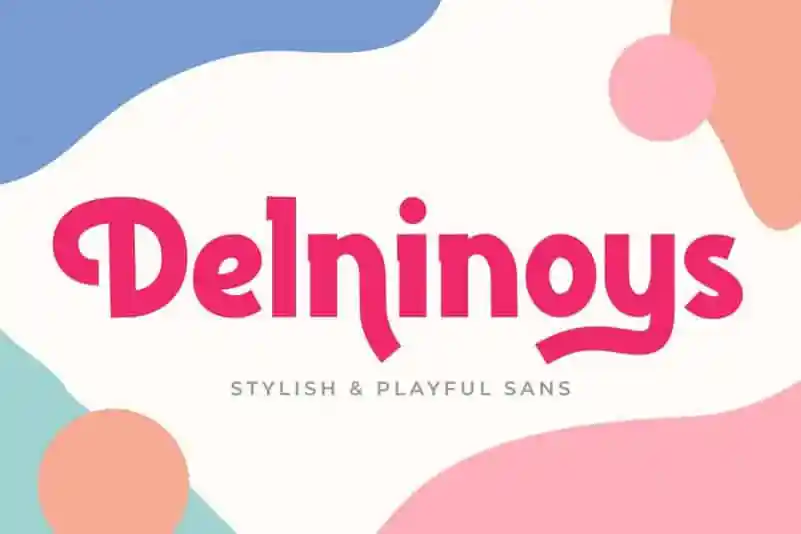
Delninoys – Stylish Playful Sans Font – Download Grátis
Delninoys é uma elegante sans-serif que se destaca por sua personalidade descontraída e seu charme casual. Esta fonte display/headline foi projetada para apresentar ideias dinâmicas no contexto de esportes ou editorial, nas marcas publicitárias e em cabeçalhos amplos. Suas linhas desenhadas com cuidado, oferecem uma aparência down-to-earth e leitura fluida, tornando-a versátil e adaptável para múltiplos contextos. Delninoys se destaca não apenas pela sua expressividade única na criação de headlines impactantes, mas também por seu uso em fundo vibrante ou como cabeçalho em si mesmo. Essa fonte é perfeita para aqueles que buscam uma alternativa fresca e desafiadora às fórmulas tradicionais de typefaces. Seja você um designer de moda, editor de revistas ou profissional da publicidade, Delninoys – Stylish Playful Sans Font oferece a oportunidade de deixar sua marca com uma linguagem gráfica que vai além do óbvio. Seu design moderno e personalizado combina elegância com originalidade, garantindo sempre um impacto visual impressionante. Não importa em qual contexto você utilize Delninoys, suas linhas dinâmicas e seu toque divertido tornarão sua criação uma verdadeira obra de arte.